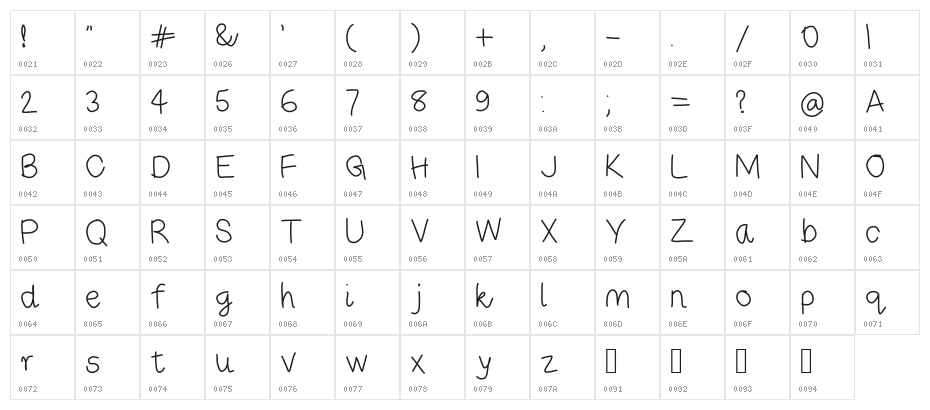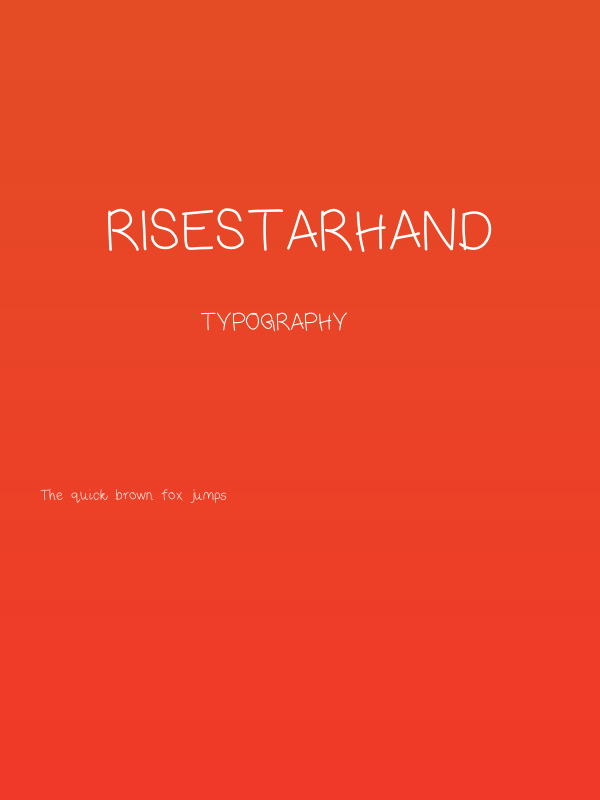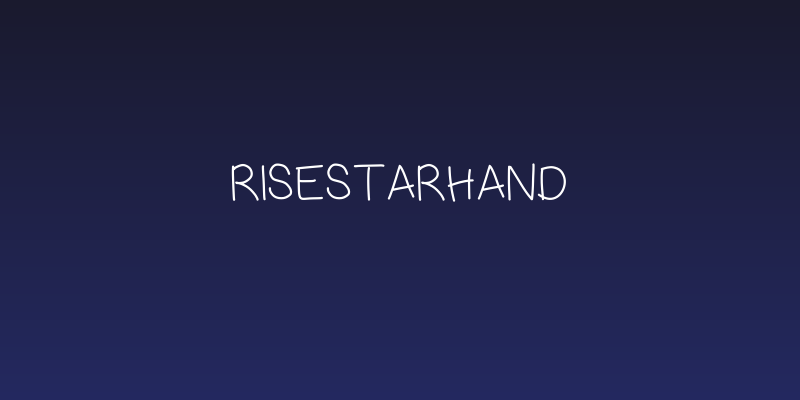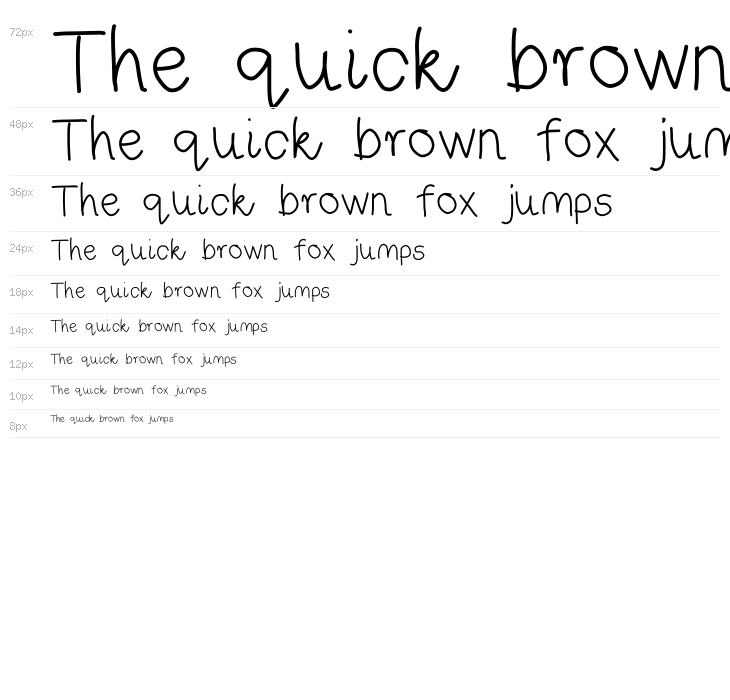
RiseStarHand Font
| Gesamtstil | Casual, Playful |
| Anwendungsfall | Headlines, Informal text, Creative projects |
| Vorgeschlagene Projekte | Ideal for greeting cards, children's books, casual branding, and social media graphics. |